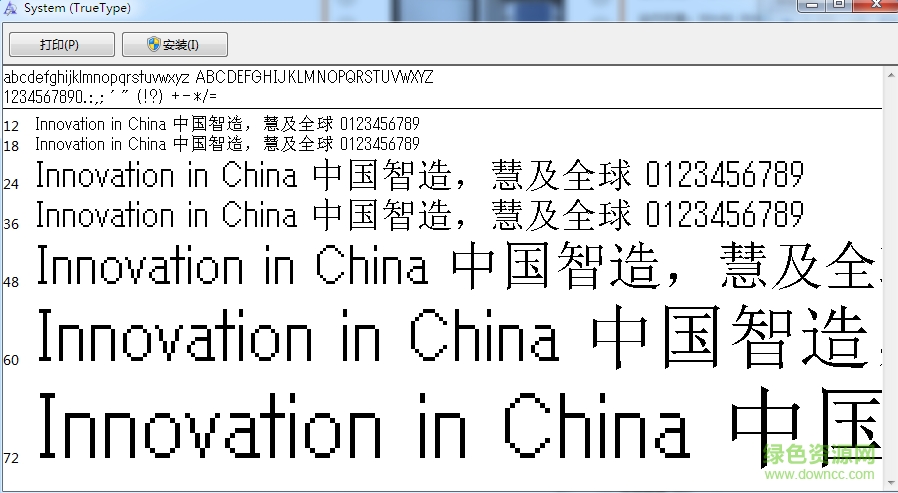
jvgasys.fon字體是一款字形優(yōu)美的電腦字體,字體簡潔大方,支持漢字數(shù)字英文等多種輸入法輸入顯示,常用于美工設計創(chuàng)作之中,有需要的朋友歡迎來綠色資源網(wǎng)下載體驗!
jvgasys.fon字體是一款應用于藝術設計方面的簡體中文字體,字體簡潔端正,廣泛適用于印刷廣告設計等多種領域,下載安裝即可使用非常便捷!